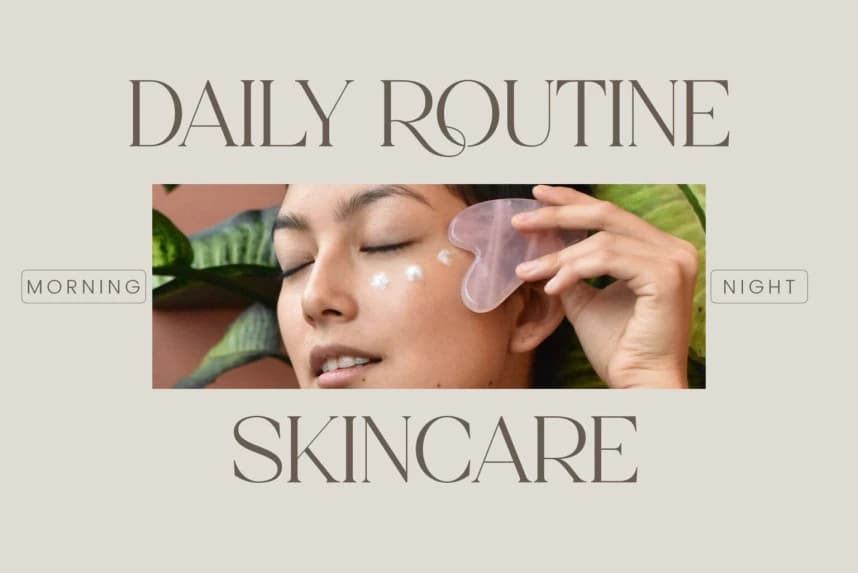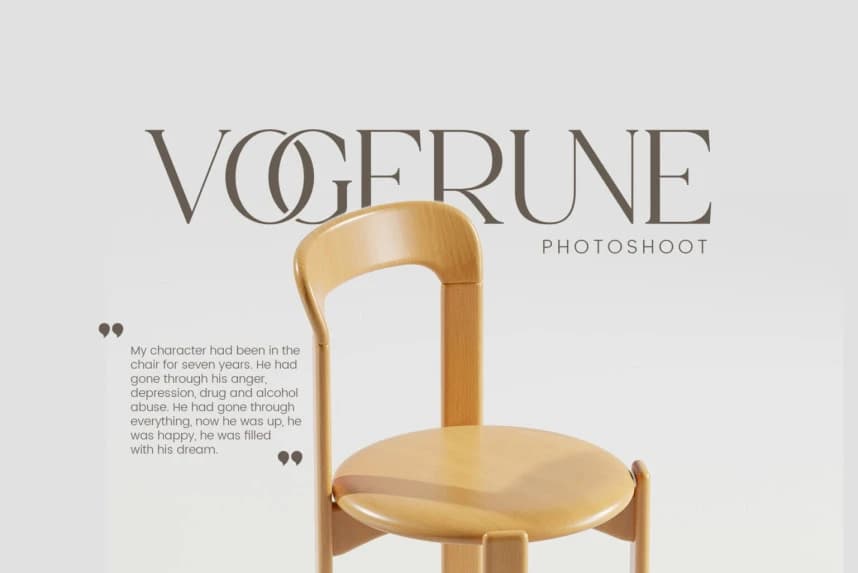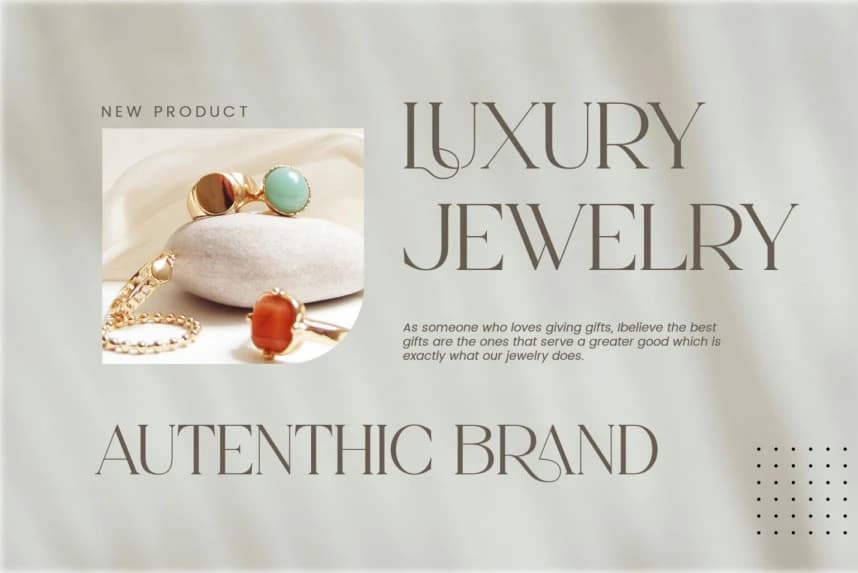
Craos Font
Craos Font - Stylish Ligature Typeface, ünlü minimalist logodan ilham alınmıştır; şablonlar, broşürler, videolar, reklam markalaşması, logolar ve daha fazlasını tasarlamak için mükemmel.
Craos Font - Stylish Ligature Typeface, ünlü minimalist logodan esinlenen ve şablonlar, broşürler, videolar, reklam markalaşması, logolar ve daha fazlası için mükemmel.